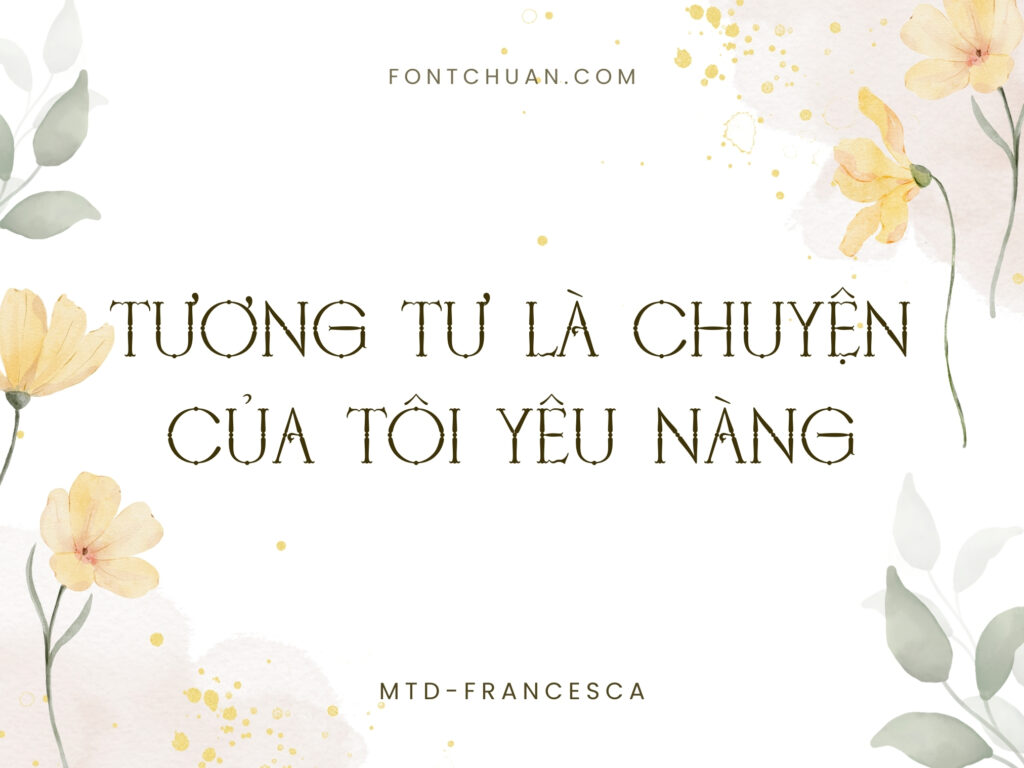
Font MTD Francesca Việt Hóa
Tác giả Font: 2D Typo
Font MTD Francesca là một phông chữ trang trí tinh tế, được thiết kế bởi Lukyan Turetskyy và phát hành bởi 2D Typo. Font đã được Việt hóa bởi Mộc Hạ, hỗ trợ tiếng Việt và hơn 90 ngôn ngữ khác, giúp mở rộng khả năng ứng dụng trong các thiết kế đa ngôn ngữ. Đây là một trong những phông chữ được cộng đồng thiết kế đánh giá cao và ứng dụng trong nhiều dự án sáng tạo, đáp ứng nhu cầu đa dạng của người dùng.
MTD Francesca nổi bật với các đường nét độc đáo, mang đến cảm giác sang trọng và lễ hội. Font rất phù hợp cho các thiết kế logo, tiêu đề, bao bì sản phẩm, thiệp mời và các ấn phẩm đòi hỏi sự tinh tế và nghệ thuật. Các ngành nghề phù hợp bao gồm quảng cáo, giáo dục, công nghệ, thiệp cưới và ảnh cưới. Font này cũng lý tưởng cho các sự kiện như Tết, Giáng sinh, Valentine và các lễ hội khác